数字时代,动态是平面最好的助推器
无论是标识、吉祥物还是运动项目图标的设计,每一届奥运会的视觉设计都会引发大量的探讨。虽然很遗憾2020东京奥运会未能如期举行,但这是奥运会历史上第一次采用动态设计,因此也收获了很大的反响。作为该系列动态图标的设计师井口皓太,第一次站到了大众面前。或许你还不是很了解他,但亦能从他的运动图标动态中感受到一种不同往常的流畅与精炼。那么是什么使他的动态设计看似简洁,却又与众不同?
井口皓太,1984年出生于日本神奈川县。2008年于武藏野美术大学基础设计学专业就读期间设立了株式会社「TYMOTE」。受赏经历包括:东京TDC 2014 - TDC奖、2015 D&AD - Yellow pencil、第94届纽约ADC奖金奖等。他的创作横跨平面、品牌和影像等多个领域,近年来以动态设计为主,在多个项目中担任创意指导工作。
在为ISSEY MIYAKE设计的展陈项目”MESSAGE”中,井口皓太对图形的动态化处理,是基于实体空间中悬挂式的展陈的方法。通过动态设计,他将现实空间与虚拟图案进行了连结。
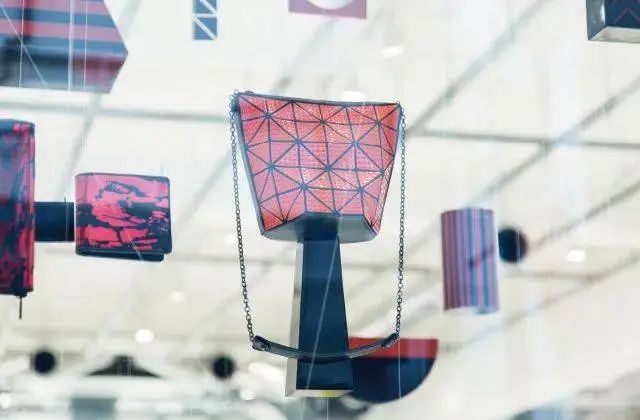
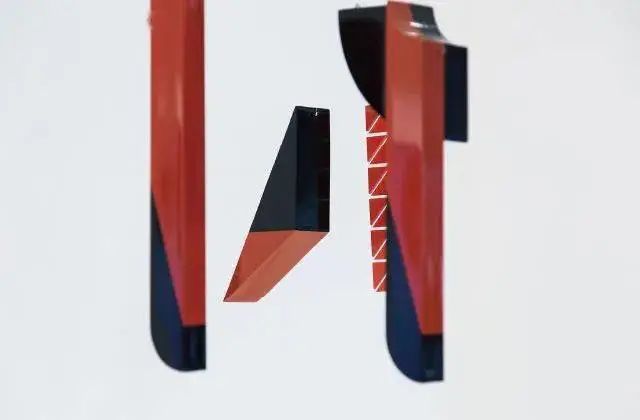
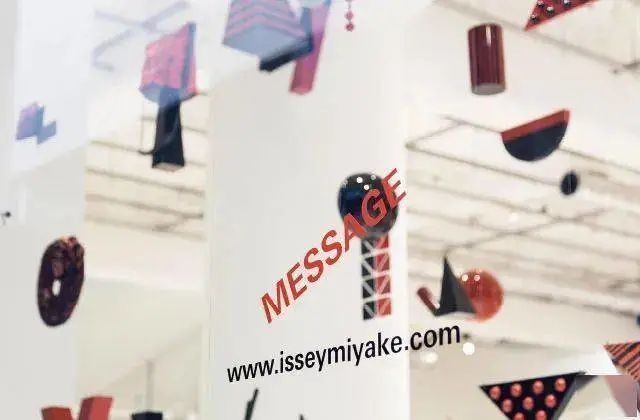
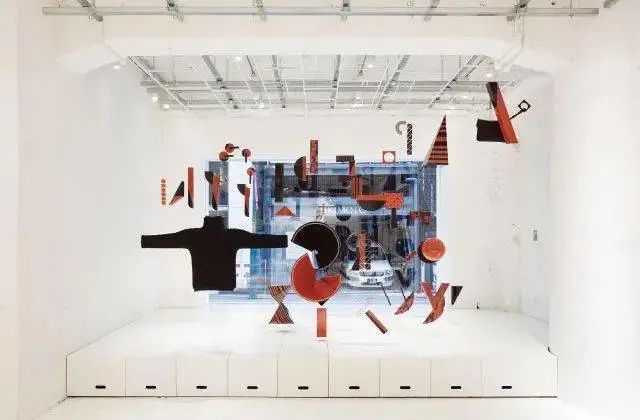
为EXPO创作的动态图形,则是根据四季中不同自然现象的运动规律,井口结合字型特点设计了系列动态。
动态所依托的新技术自身无疑有着很大的魅力,毕竟技术总是令人着迷的,它意味着无限的可能性和趣味感。然而设计的主旨并非为展现技术存在,对于动态设计来说,更好的传达创意才是其目的。井口皓太的作品也正因非常擅长用合适的技术配合相应的创意想法,才得以与众不同。
作为从平面设计学科出发,转而投入动态设计领域的设计师,井口皓太对平面与动态两者的关系有着非常独到的个人理解。他认为,如何以动态增添原有平面的光彩、丰富其内涵,而非有损平面设计的品质,是在处理二者关系时,最难做到也必须做到的事。这种认知在2020东京奥运会动态图标与静止图形高度适配的状态中就有所体现。
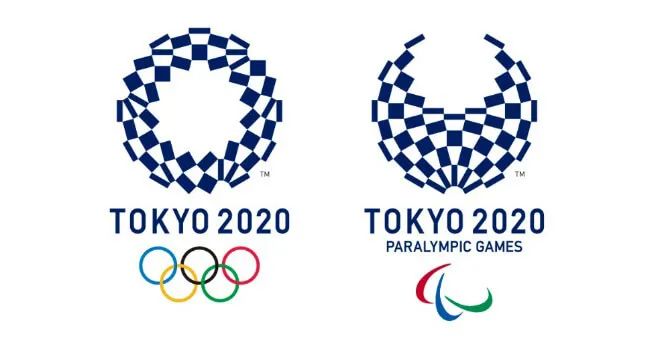
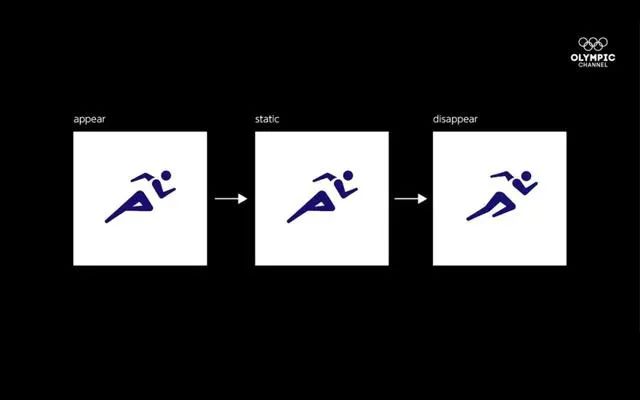
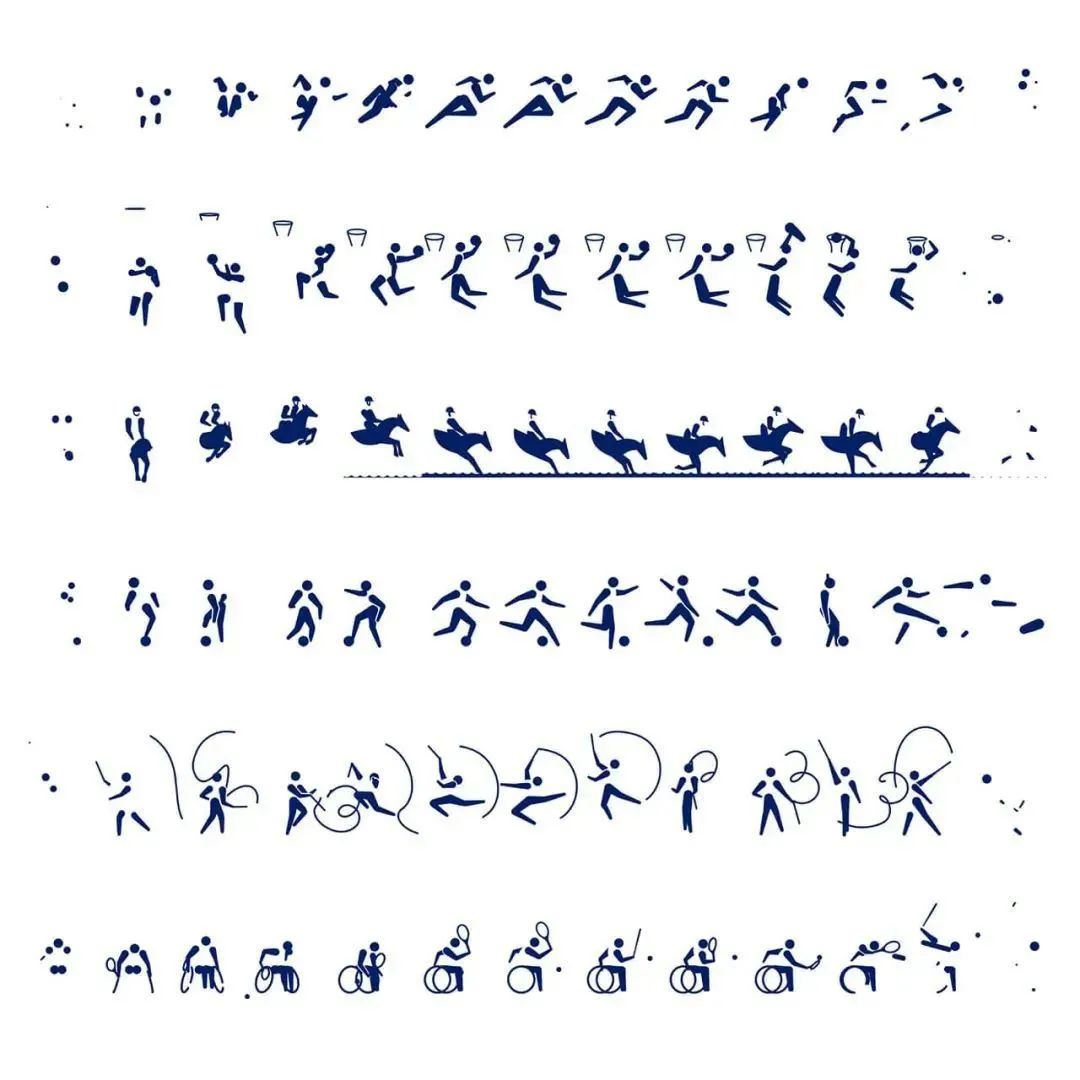
事实上,2020东京奥运会的图标是基于1964东京奥运会图标的再设计,后者开创了奥运会第一次采用运动项目图标的先河,而前者是则是第一次试着让图标动起来。在某种程度上,两次尝试都是日本设计为奥林匹克注入现代设计的创新挑战。
运动本身就是一个动态的过程,通过这种具有美感且容易理解的方式,动态图标更全面地传达了每一项运动的魅力。在这个项目中,动态是平面最好的助推器。“动态平面,某种程度上来说亦还是平面设计的一个种类。”
在信息爆炸的今天,媒体的形态已经发生了改变。各式各样的电子屏幕承载的不仅仅是静止的信息,而使信息带上了流动的性质。但这是否意味着动态终将取代平面?
井口给出的答案是否定的。以其获得TDC设计奖的作品「kanji city」为例,「kanji city」原本是在运动馆为骑行自行车时观看所用而制作的动画。因此画面的韵律,非常符合人在运动时的呼吸节奏。画面中,则是将汉字本身的含义与字形相结合,用树,河,寺,门等16种汉字构成京都的多个场景。
在作品中,井口用二维的动态表现出三维的空间感,让平面设计在空间与时间中流动,从而让图形变得更立体、活跃、生动。相比使用精良渲染技术和建模后完成的动态设计,他的作品似乎更像是平面设计在空间和时间线上的延伸。
在过去,技术的限制培育了设计师对于信息提炼的能力,将信息凝结于一个微观的图形和符号是平面设计的目的之一。而现在,动态越来越被需要,如何将信息置于越发走向多变化的流动世界,成为了当下设计师必须面临的挑战。时至今日,与其说动态终将取代平面,倒不如说动态设计是平面设计的一种延伸。